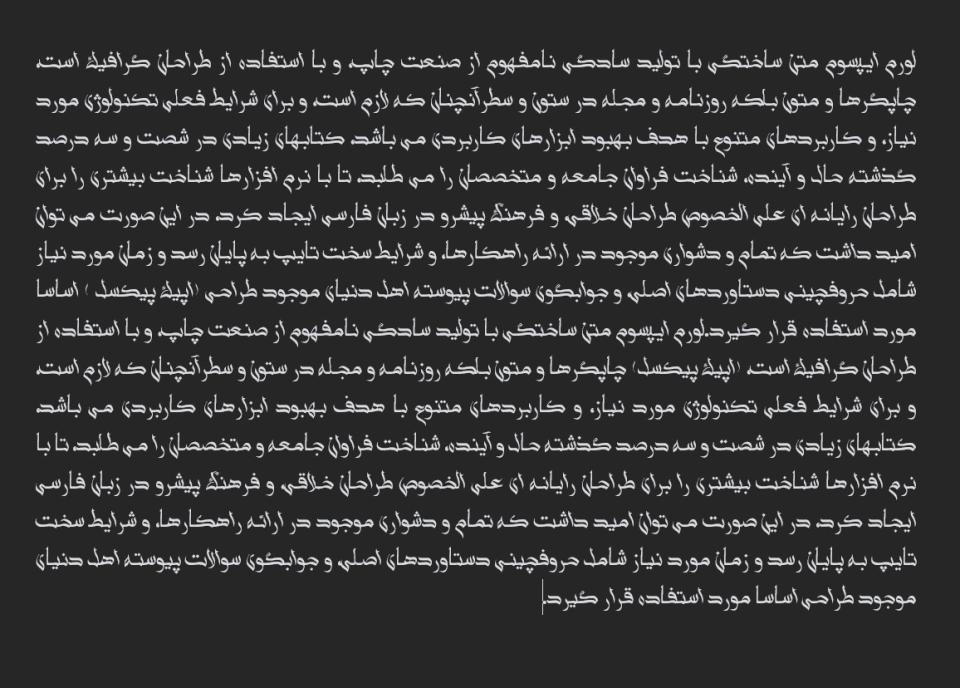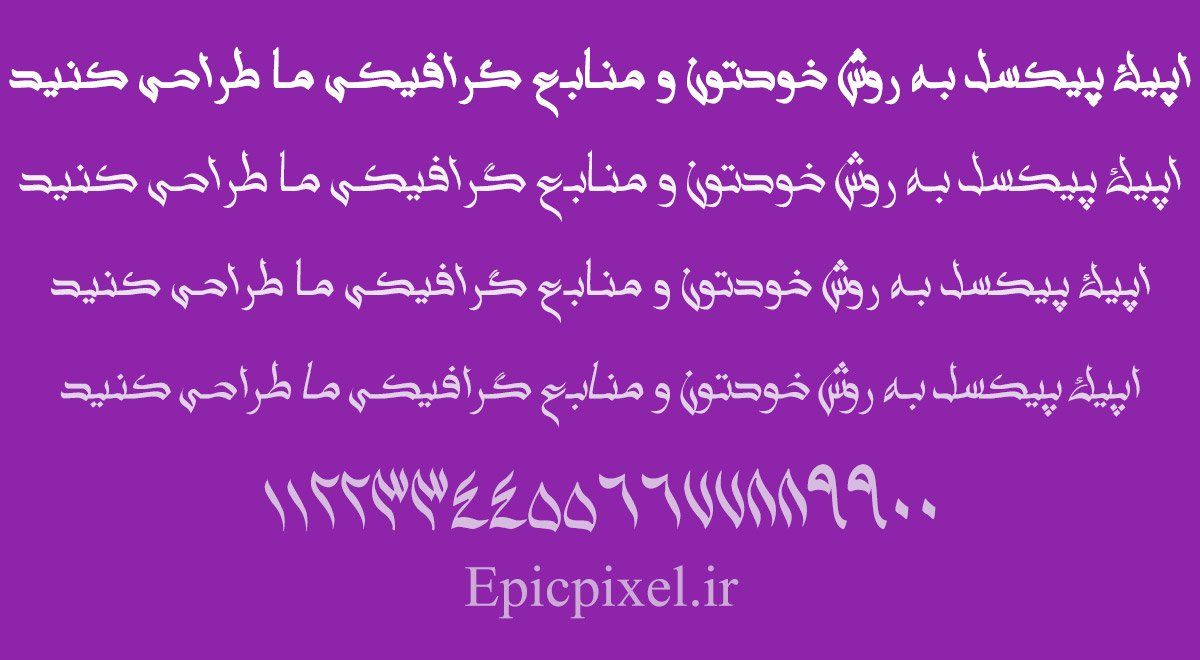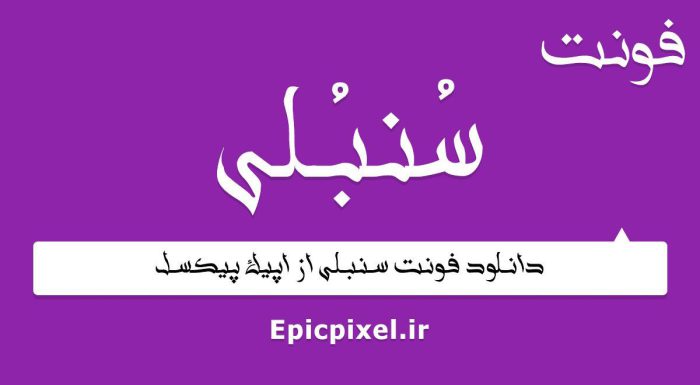
فونت سنبلی فارسی عربی Sonboli
فونت سنبلی فارسی، با ظاهری خاص و متفاوت، می تواند جلوه ای نو به نوشته های شما ببخشد. این فونت با حروف موج دار و بهم ریخته اش، حسی از دست نوشته های قدیمی و اصیل را القا می کند. تصور کنید متنی را با این فونت طراحی کرده اید؛ ناخودآگاه توجه مخاطب را به خود جلب می کند و حس کنجکاوی او را برمی انگیزد.
یکی از ویژگی های برجسته فونت سنبلی، همین ظاهر نامتعارف آن است. در دنیایی که بیشتر فونت ها به دنبال نظم و ساختار هستند، سنبلی با جسارت، مسیری متفاوت را در پیش گرفته. این ویژگی باعث می شود تا طراحی های شما از حالت یکنواخت و خسته کننده خارج شده و شخصیتی منحصربه فرد پیدا کنند. به عنوان مثال، اگر در حال طراحی پوستر یا کارت دعوتی با حال و هوای سنتی و قدیمی هستید، فونت سنبلی انتخابی ایده آل خواهد بود.
البته این ظاهر خاص، ممکن است برای هر نوع متنی مناسب نباشد. به دلیل بهم ریختگی حروف، خوانایی متن در اندازه های کوچک ممکن است کمی دشوار باشد. بنابراین، توصیه می شود از این فونت بیشتر در عناوین، تیترها و نوشته های کوتاه استفاده کنید تا هم زیبایی آن به چشم بیاید و هم خوانایی متن حفظ شود. در واقع، بهترین کاربرد این فونت در جاهایی است که می خواهید تاکید ویژه ای روی متن داشته باشید و نگاه مخاطب را به خود جلب کنید.
فونت سنبلی عربی فارسی